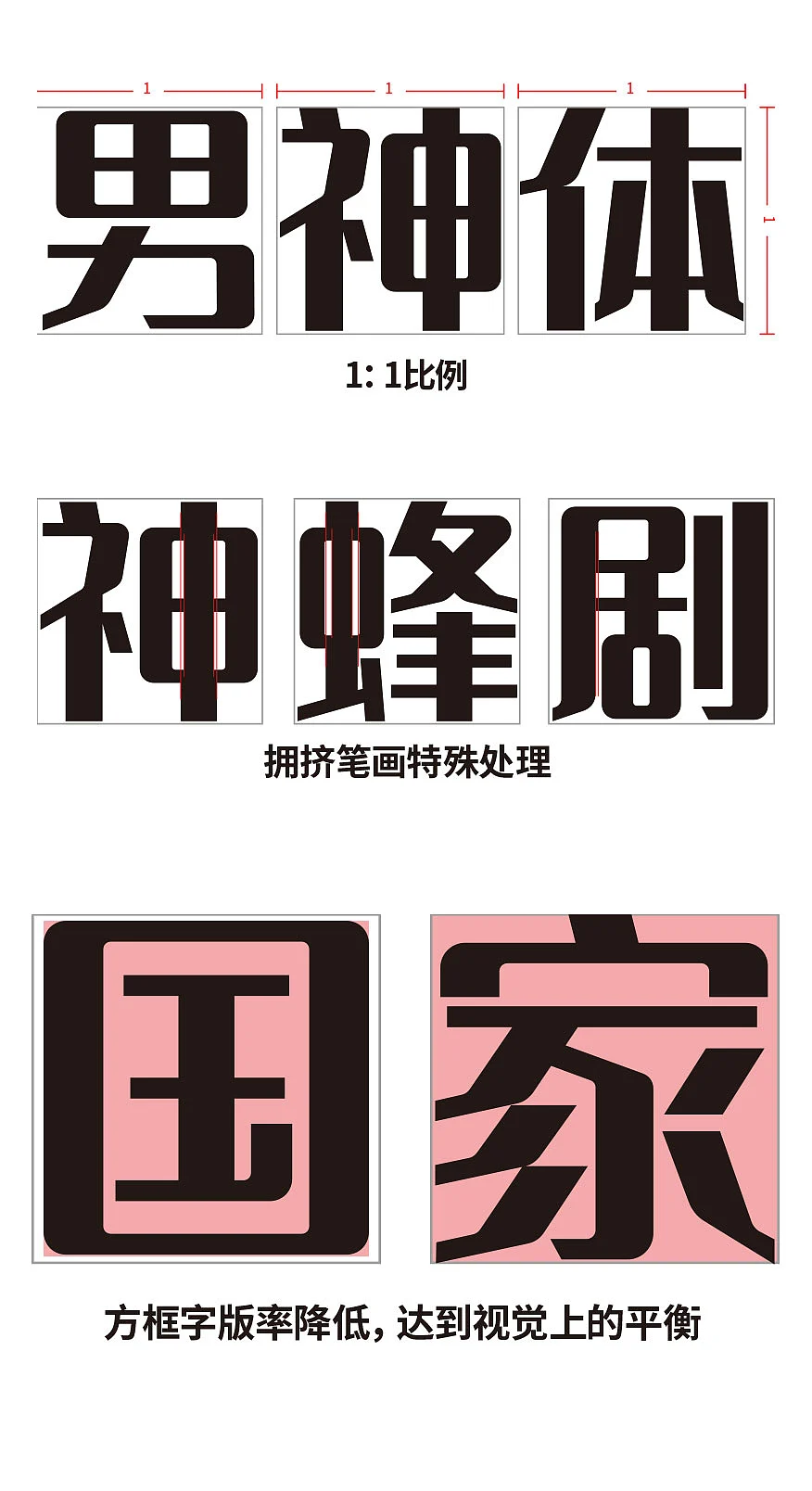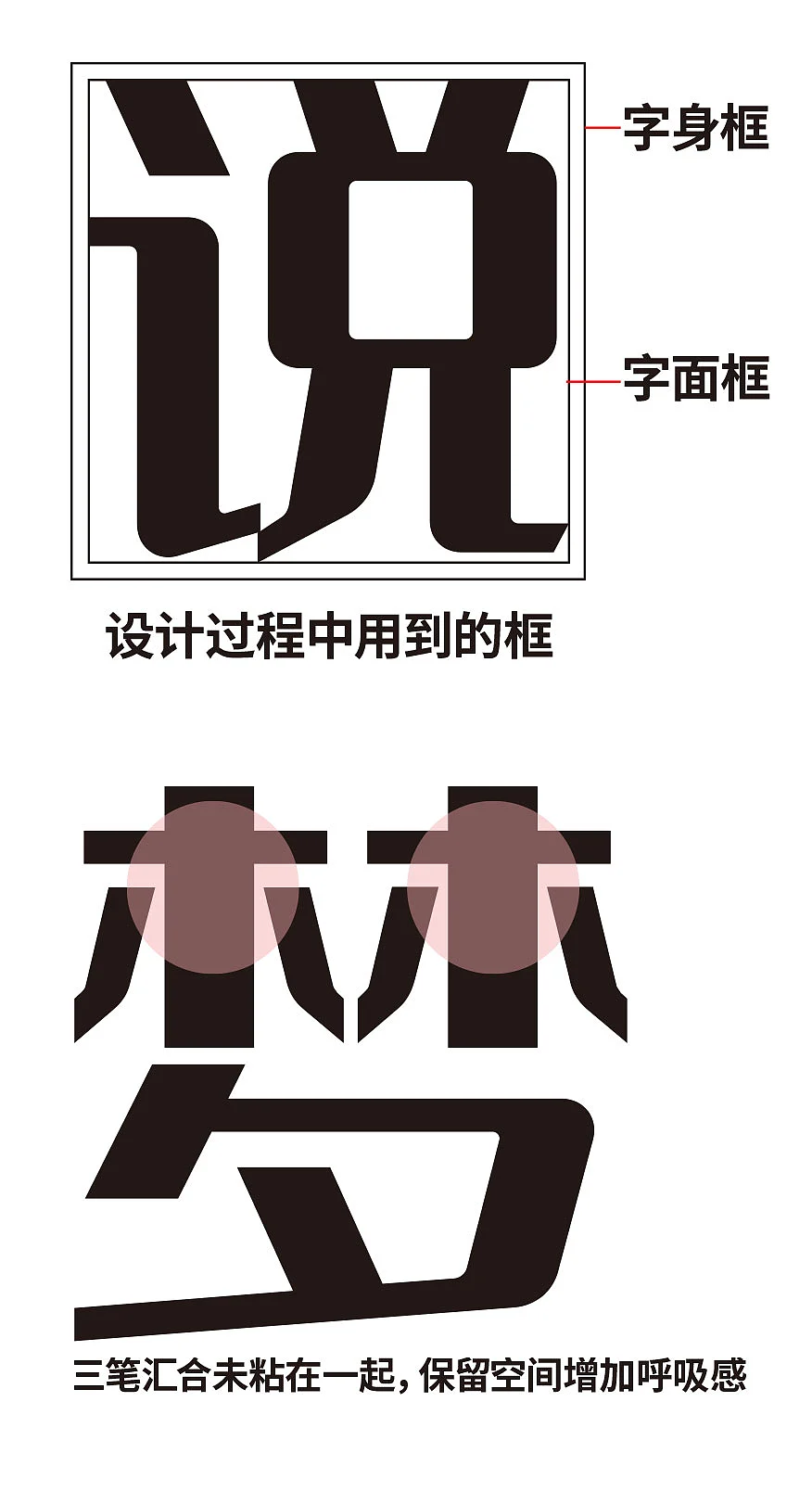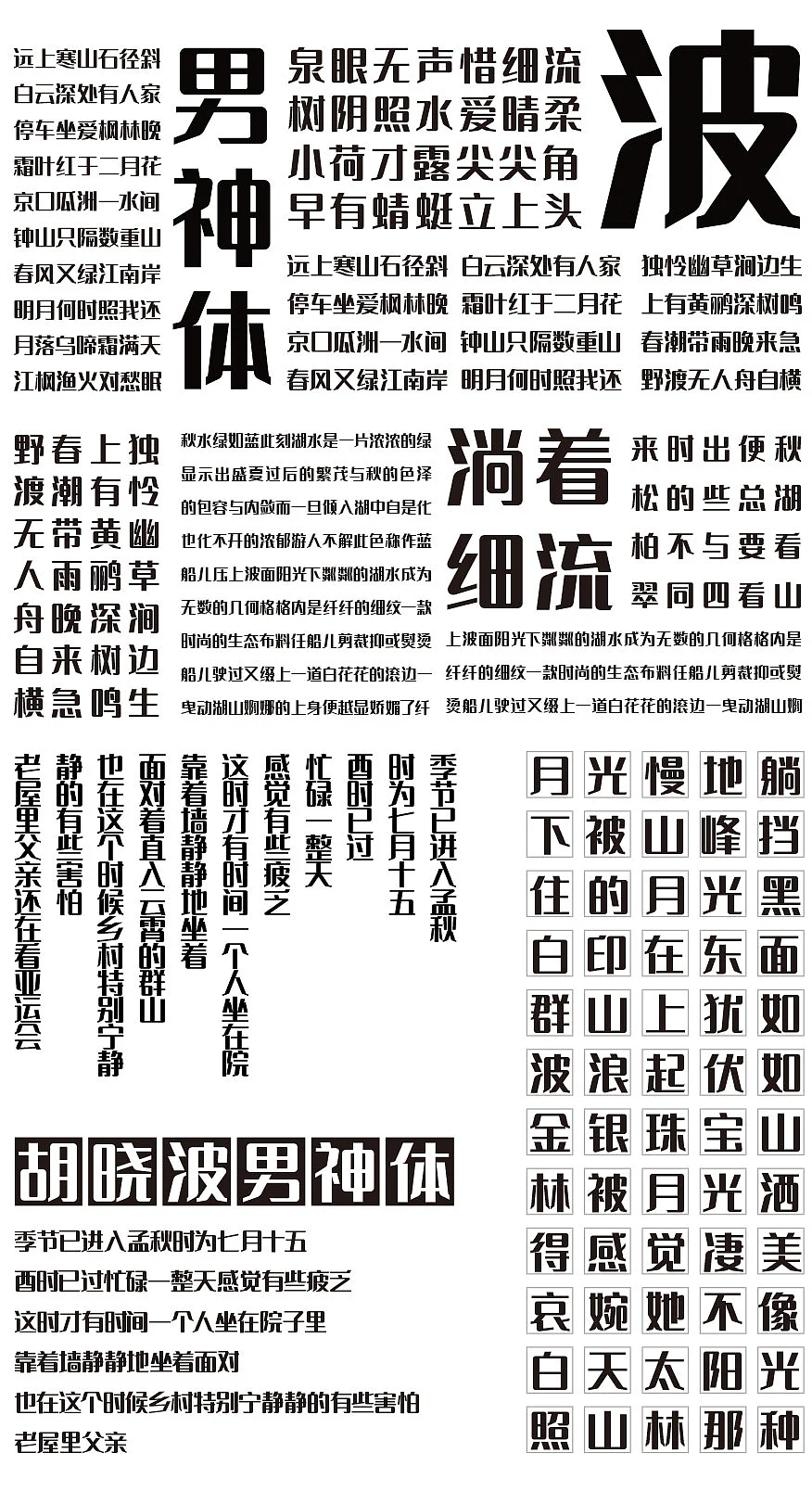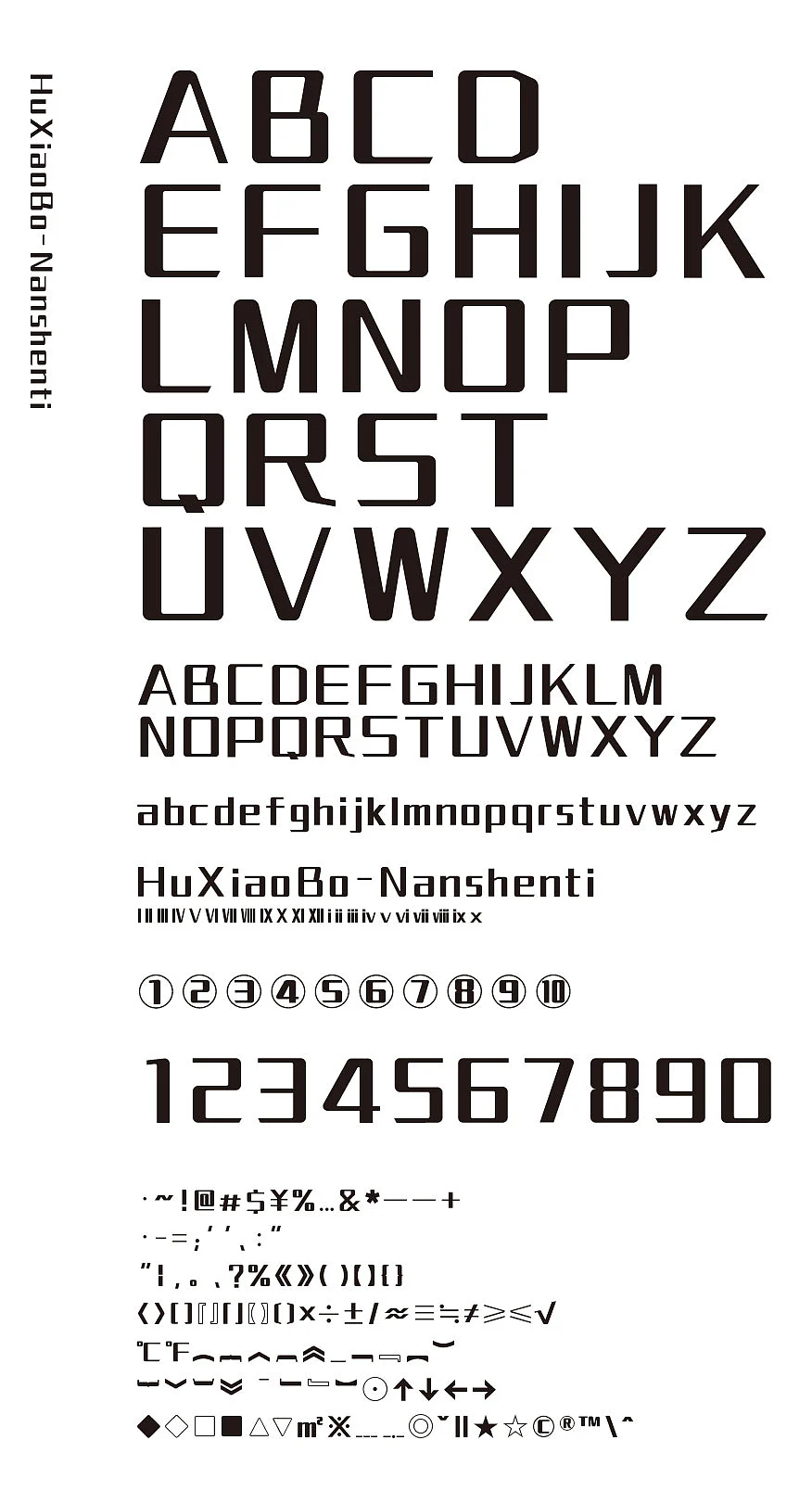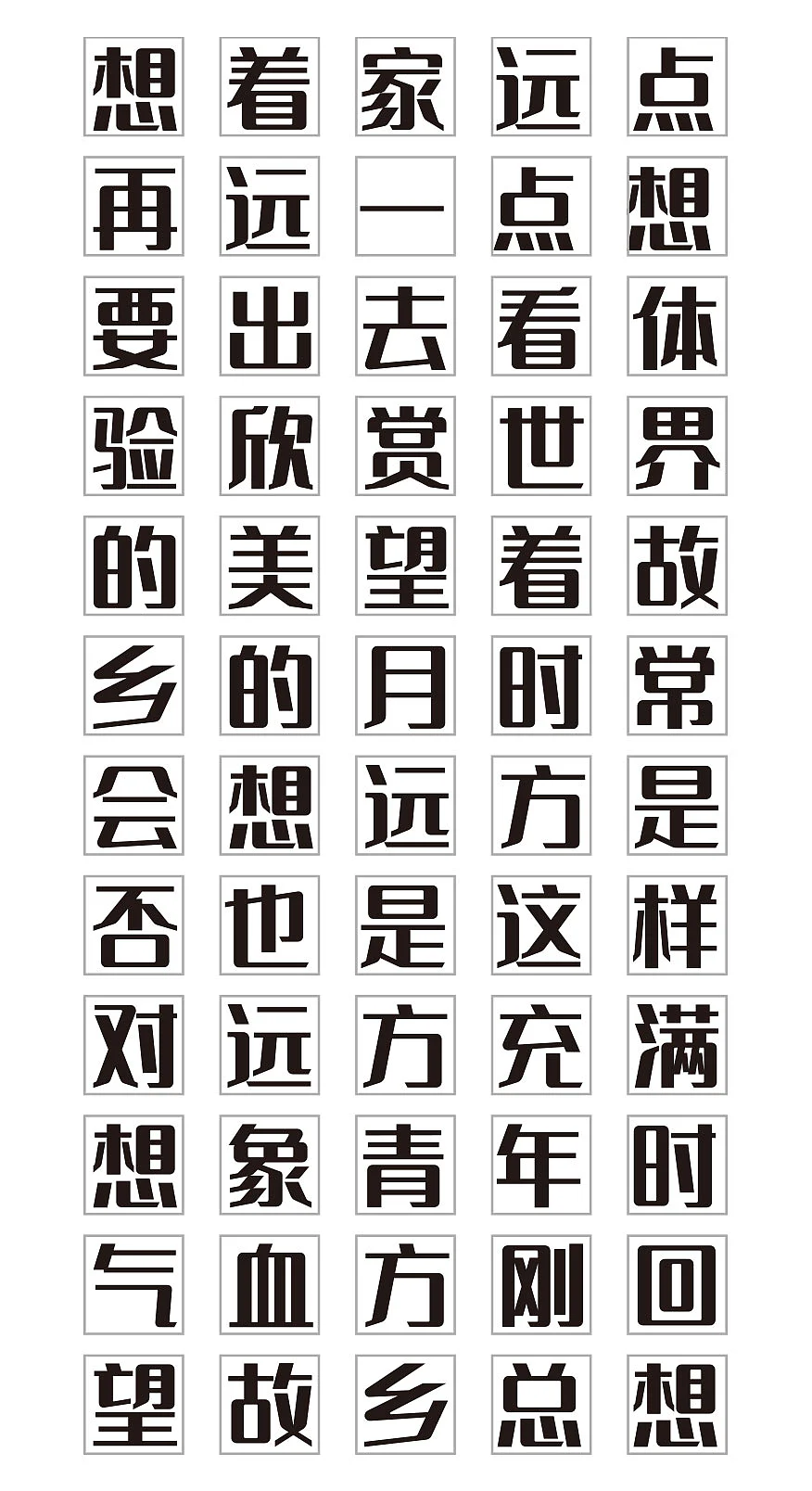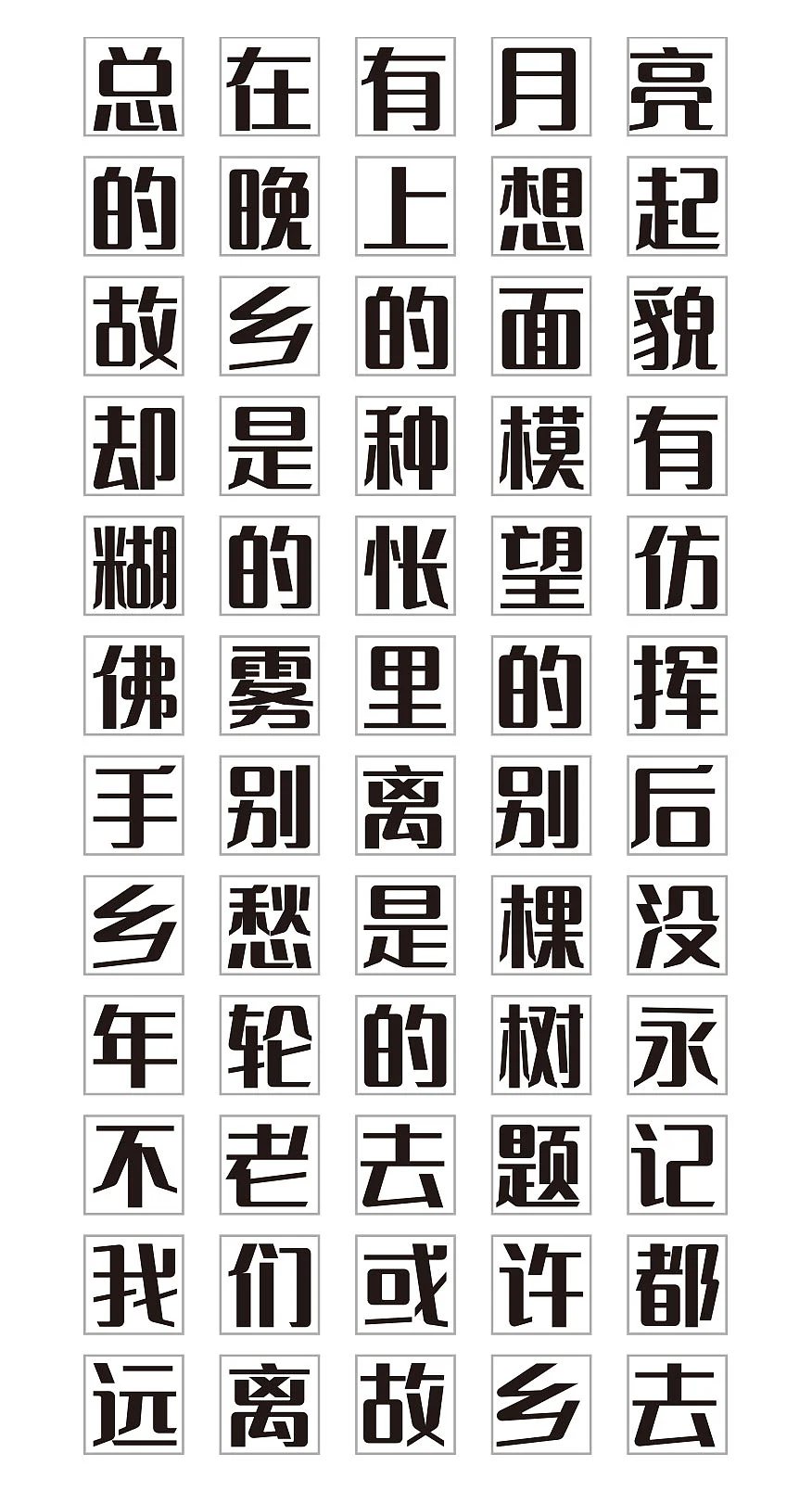
胡晓波男神体
胡晓波男神体是设计师胡晓波在从业十年之际,推出的三款免费商用字库之一(另外两款为胡晓波真帅体、胡晓波骚包体),三款字体均已在国家版权局完成登记认证,以字库形式分享设计经验,回馈设计社区。
胡晓波男神体采用1:1 等宽比例,字形方正饱满,笔画粗壮有力,兼具现代感与力量感。对拥挤笔画进行特殊处理,避免了笔画堆叠导致的视觉杂乱,保证了清晰的识别性。降低方框字版率,通过调整字面框与字身框的比例,让字形在视觉上更平衡,避免了传统方块字的刻板感。三笔汇合处刻意不粘连,保留细微空间,增加了字体的呼吸感与细节层次,整体气质沉稳大气又不失精致。
作为胡晓波设计十年的诚意之作,这款字体不仅是个人设计经验的沉淀,也凝聚了工作室团队的心血,体现了设计师 “分享价值、回馈行业” 的初心。在站酷平台的支持下,胡晓波将自己的设计思考与实践转化为普惠性的字库产品,让更多人能免费使用专业级中文字体,推动设计行业的版权意识与创作生态升级。
因风格现代、结构稳定,胡晓波男神体可广泛应用于品牌视觉、宣传海报、数字界面、包装设计、办公文档等场景,既能作为品牌标识的核心字体,也能在长文本排版中保持清晰易读,适配从互联网产品到实体物料的多元需求。
作为一款兼具专业度与公益属性的免费商用字体,胡晓波男神体既满足了专业设计的表现力需求,又为中小团队与个人创作者提供了优质的免费字体选择,是设计力量普惠化的生动实践。